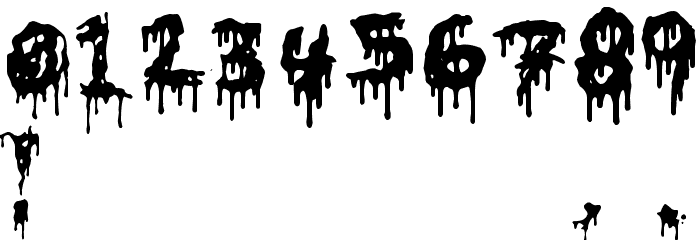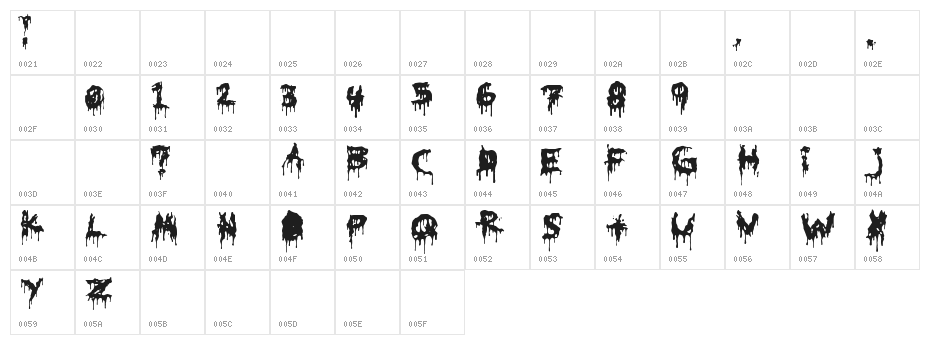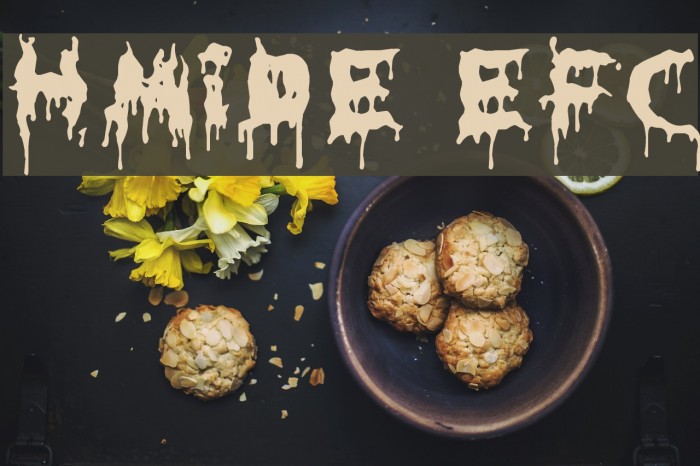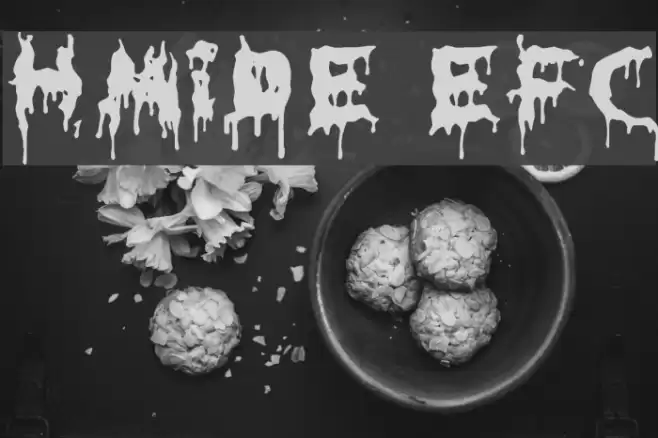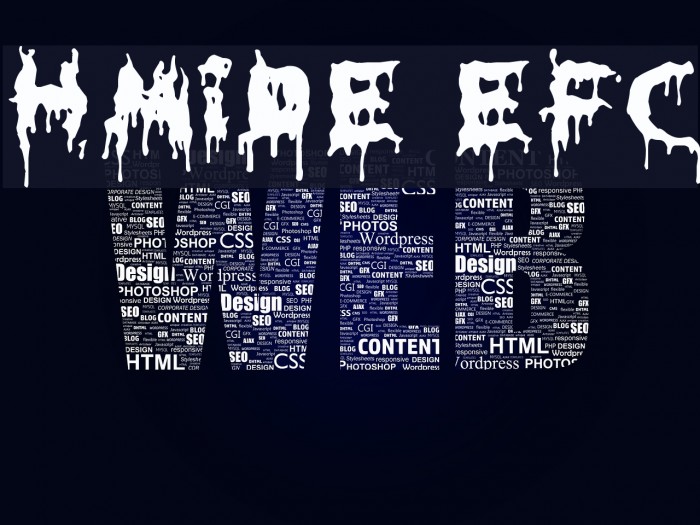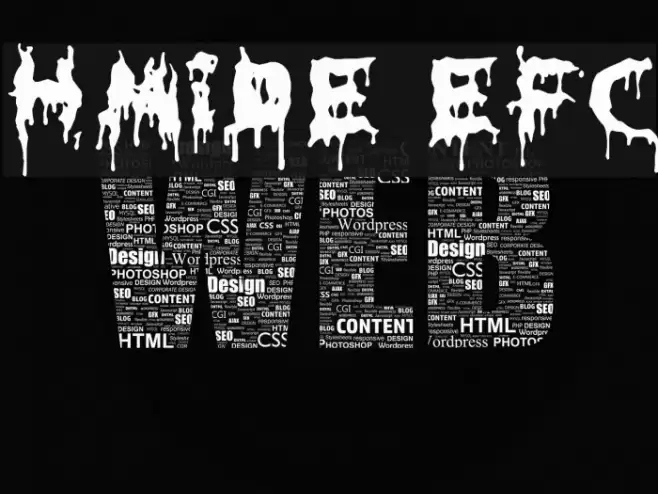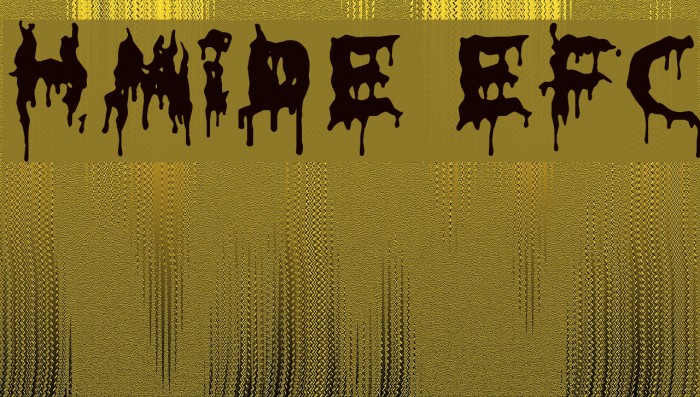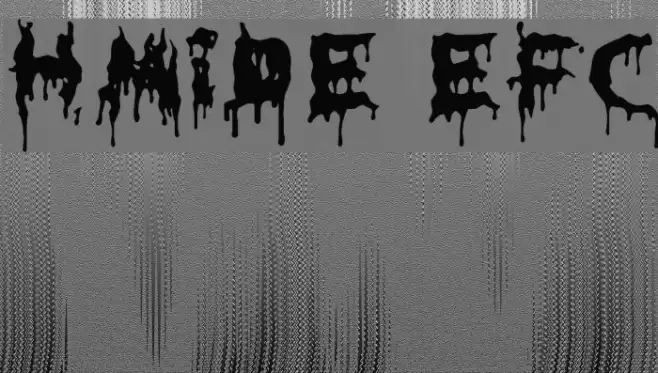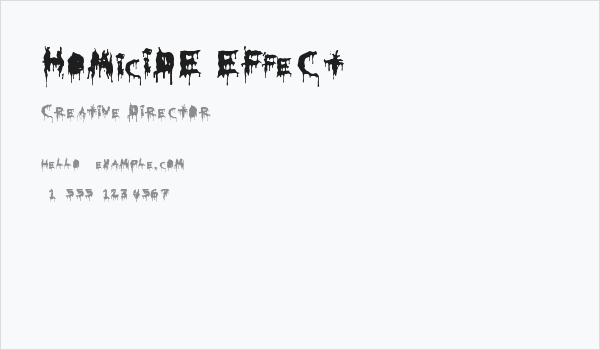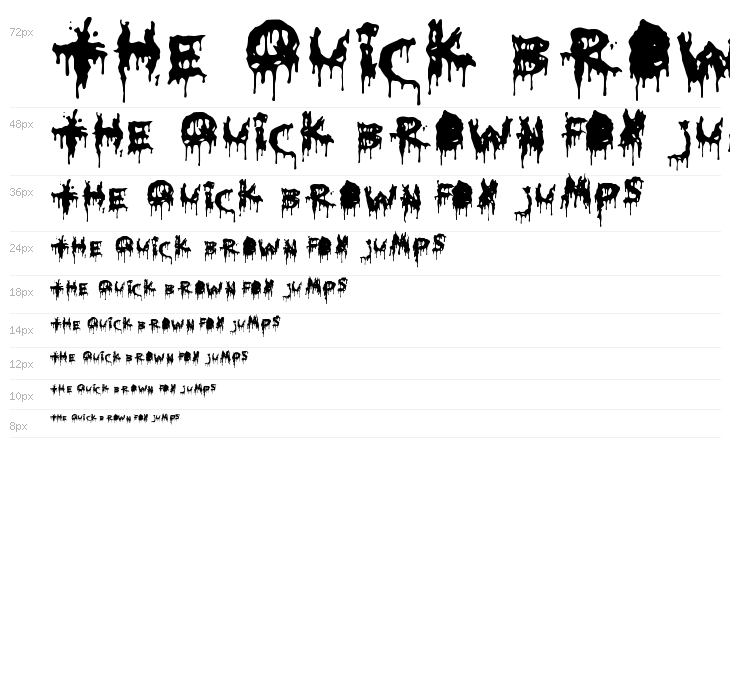
HoMicIDE-EFfeCt Font
| Vorgeschlagene Projekte | Ideal for Halloween posters, horror movie titles, haunted house flyers, and spooky-themed event invitations. |